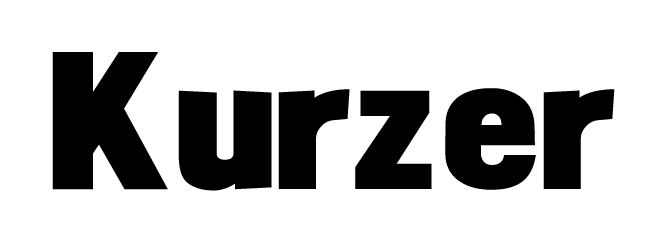
schrecklich „besoffene“ Schrift
Ich suche wahrscheinlich einen freewarefont.
„Besonders“ ist dass die Schrift ein ganz schreckliche Ausrichtung hat. Naja ich such sie für ein Projekt. Es wäre toll, wenn irgendjemand diese Schrift kennt